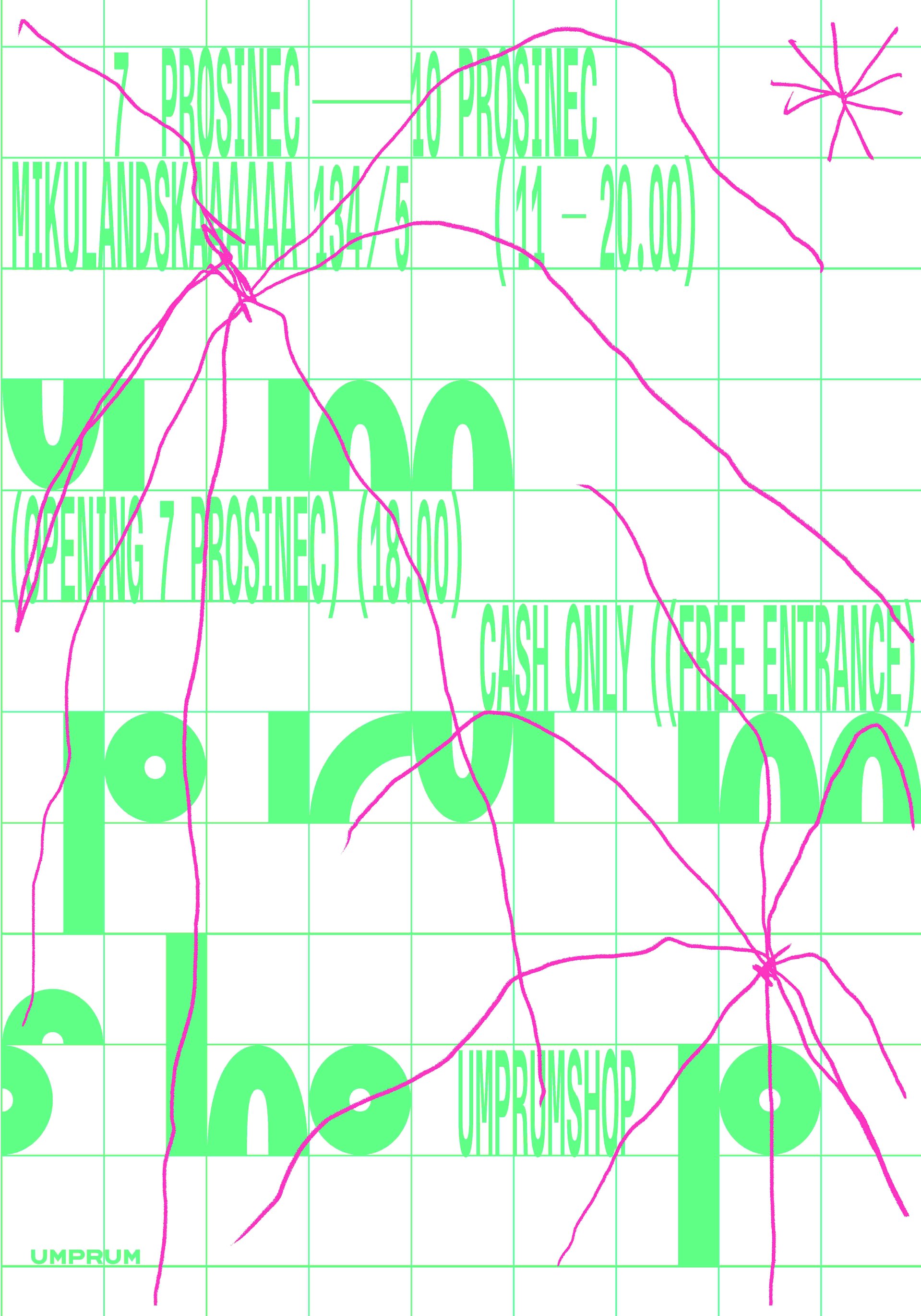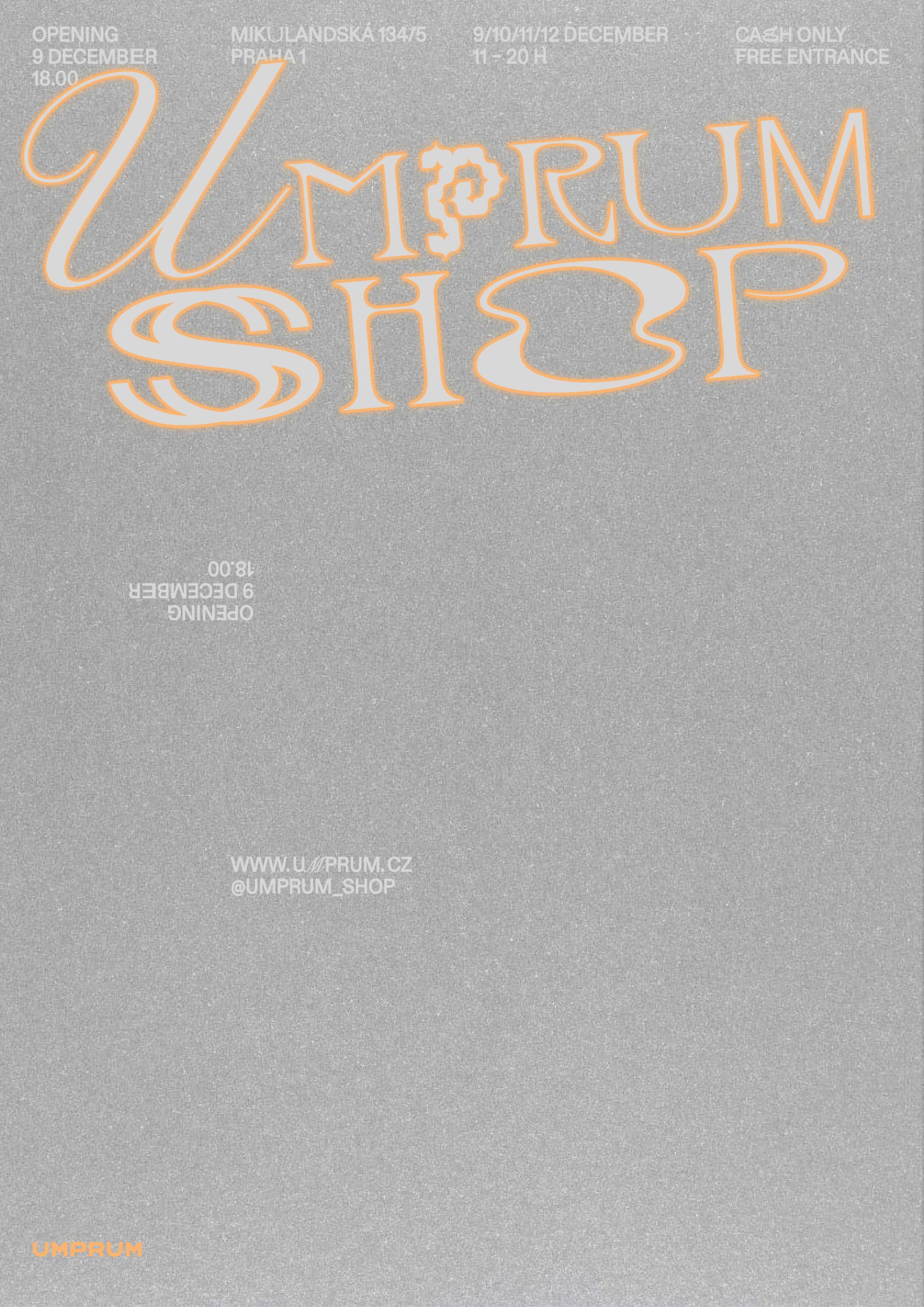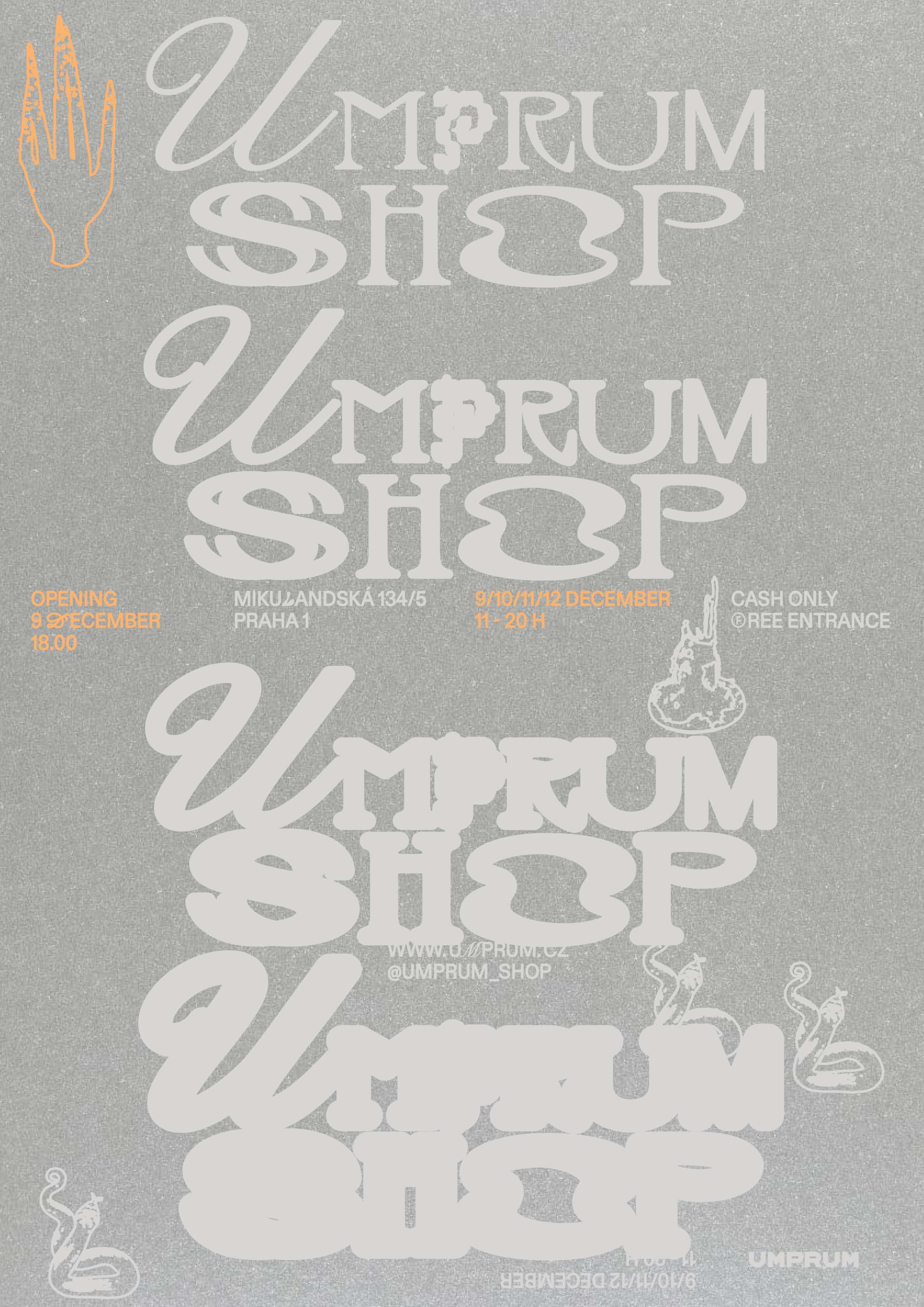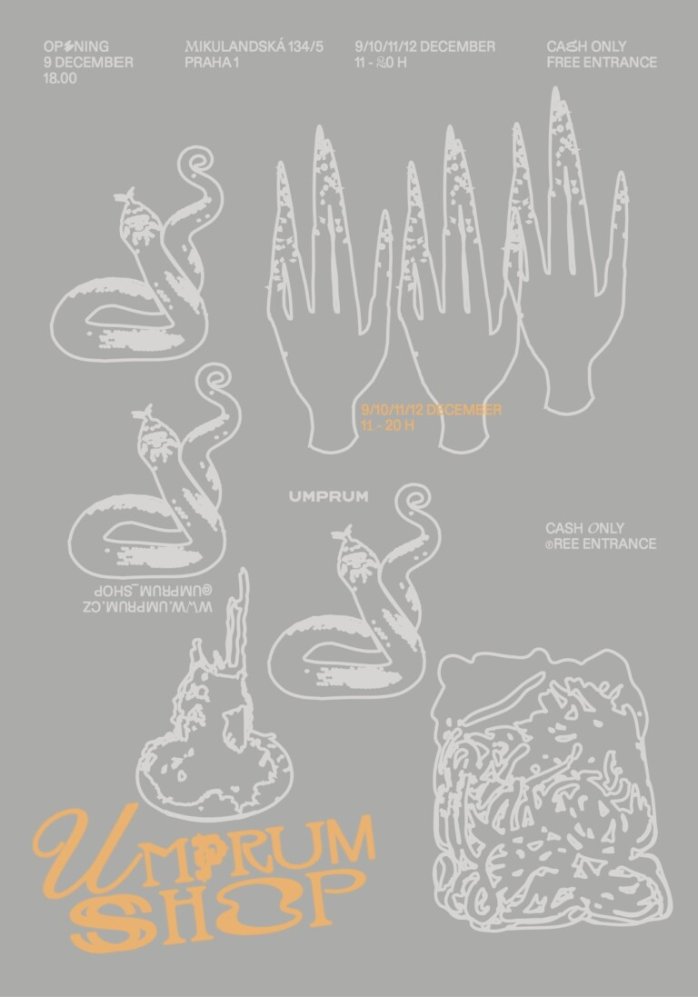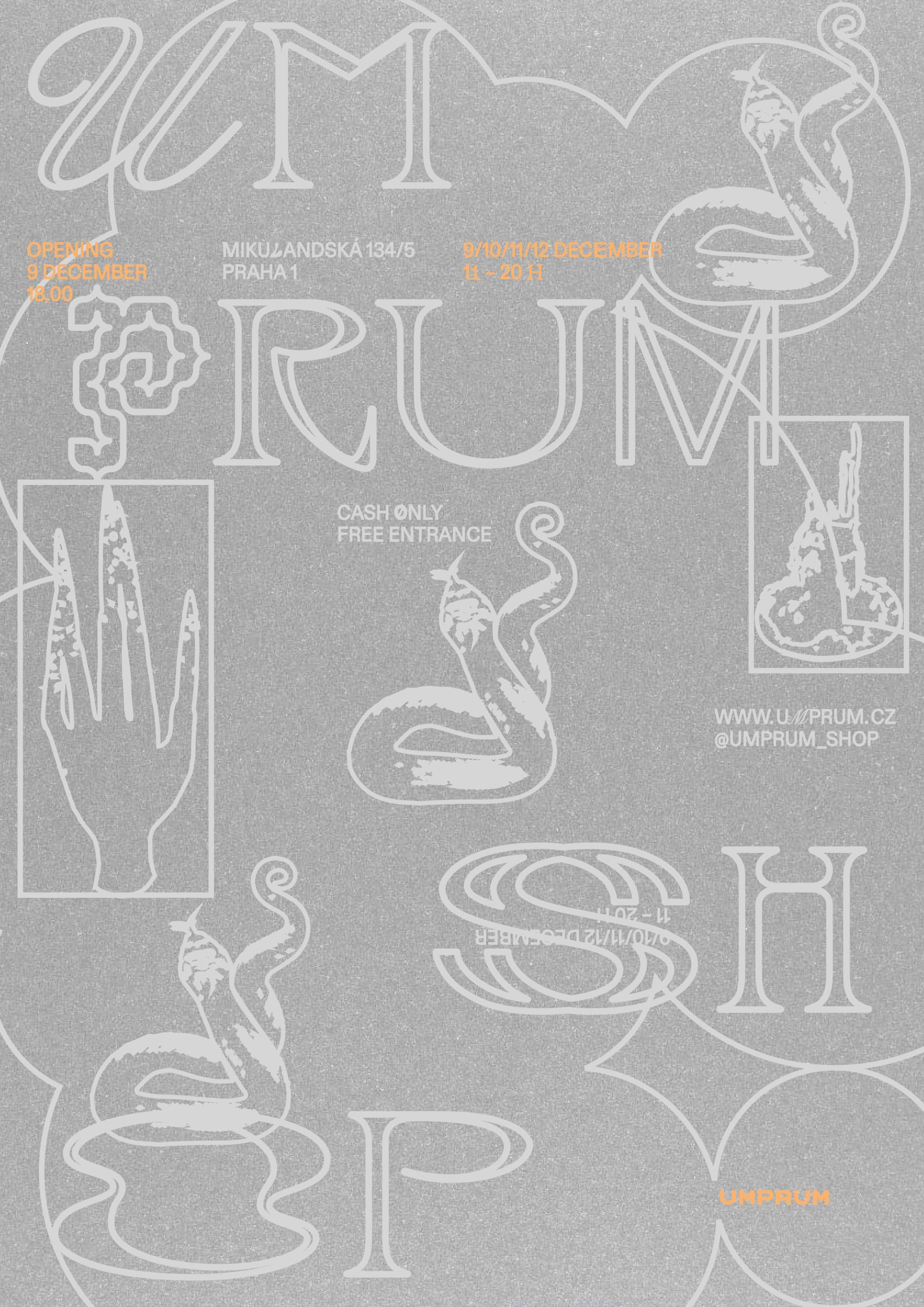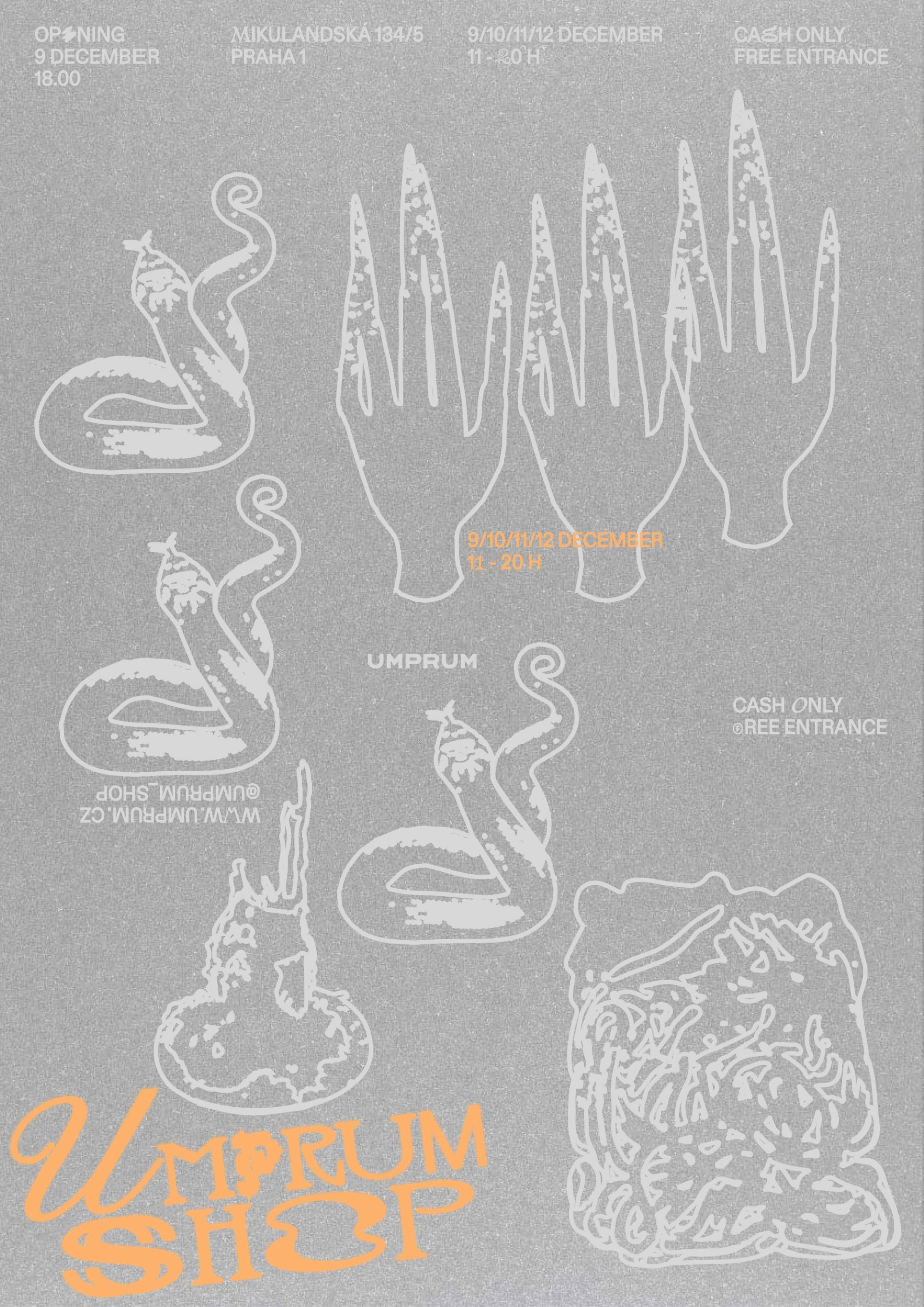
Plakáty pro předvánoční market UMPRUMSHOP absolventky Ateliéru tvorby písma a typografie UMPRUM Laury Horňak Morovské byly vybrány do mezinárodní selekce plakátů v rámci poster festivalu ANDNOWEAST. za sérii plakátů, které připravila pro předvánoční market studentek a studentů UMPRUM Umprumshop 2023 a Umprumshop 2024.
Laura na festivalu představila hned dvě série plakátů reagujících na dané téma Umprumshopu, a to pro ročník 2023 a 2024. K oběma přistupovala s odlišným přístupem. První série vizualizuje téma dětství – přísný grafický rastr autorka proměnila v hravé hřiště, kde neonové barvy a ilustrace ilustrátorky Stázky Rainishové spojují strukturu s dětskou volností.
Druhé série zkoumá téma snů a kombinuje autorčiny surreálné ilustrace s fluidní typografií. V tomto případě pracovala se stříbrným papírem a oranžovými akcenty, aby vizuál navodil atmosféru, kde se stírá hranice mezi realitou a podvědomím.
U obou prací pracovala autorka s technikou sítotisku.
ANDNOWEAST je festival a kurátorská přehlídka plakátů designérů z východní a střední Evropy, za kterou stojí organizace Local Design Circle. Hlavní myšlenkou projektu je zkoumat vizuální identitu, kulturní kontext a „genius loci“ tohoto regionu a zapojovat je do celoevropského dialogu.
Pro UMPRUM jde o prostředí, ve kterém má škola dlouhodobě silné zastoupení – v předchozích ročnících byli do výběru zařazeni například i naši absolventi Jiří Mocek a Cindy Kutíková. Letošní ročník je o to výjimečnější, že v mezinárodní porotě zasedly hned dvě výrazné osobnosti spojené s UMPRUM – designér a pedagog Radek Sidun a již zmíněný designér a absolvent Jiří Mocek
Aktuální ročník odstartoval úspěšnou výstavou v bulharské Sofii a na podzim letošního roku se celá expozice přesune do rumunského města Temešvár (Timișoara). Jde o skvělou příležitost k mezinárodní prezentaci školy a jejímu propojení s evropskou designérskou scénou.